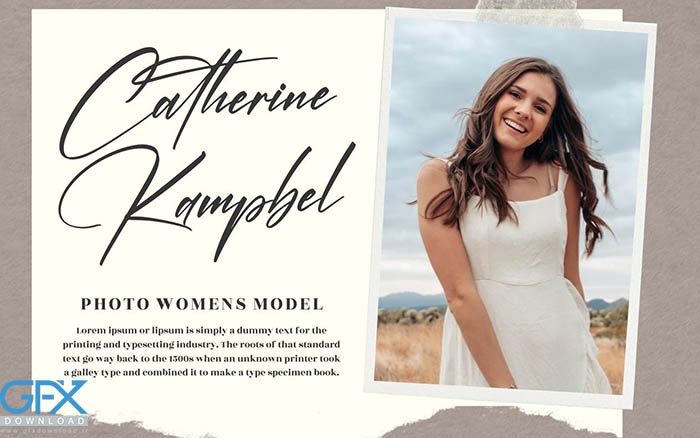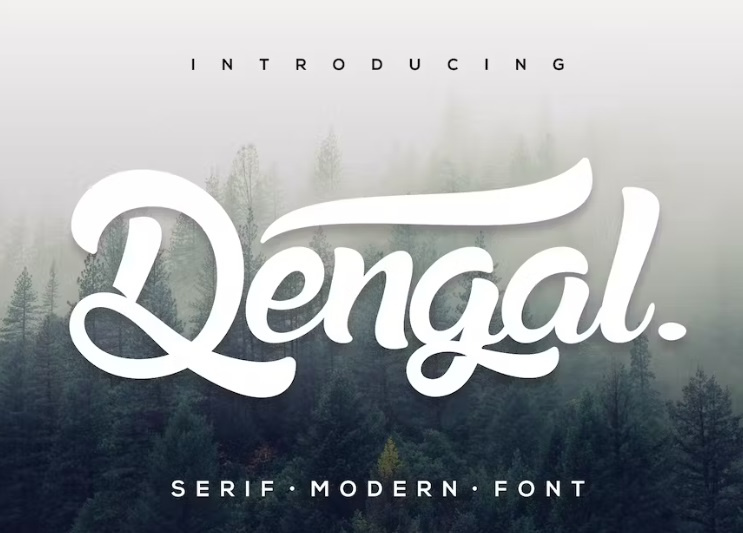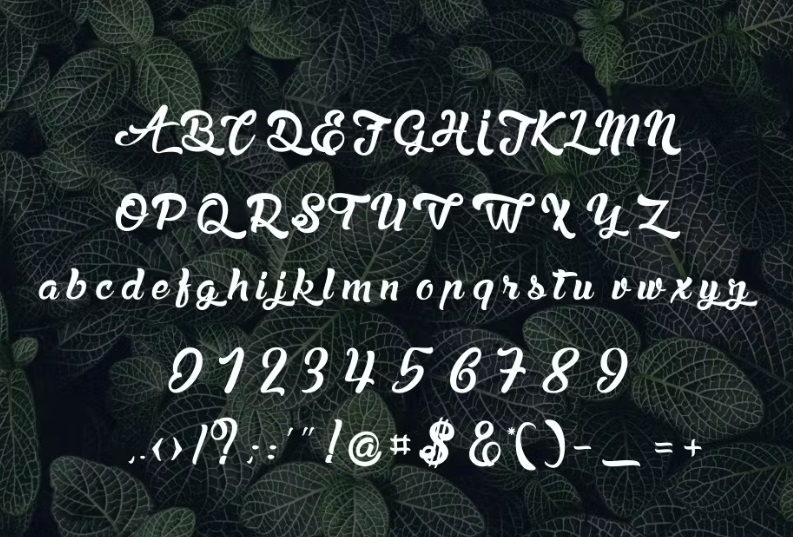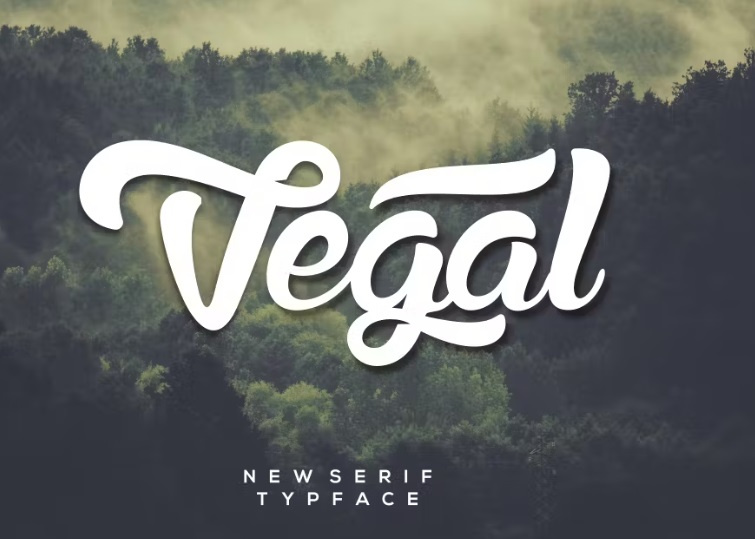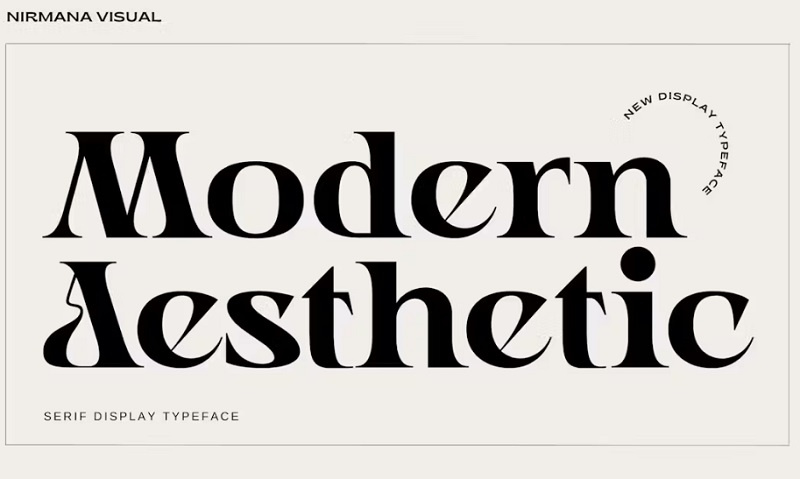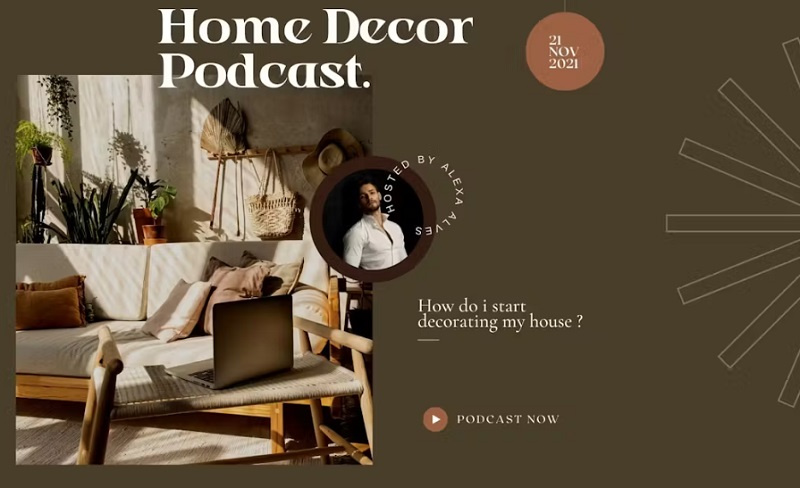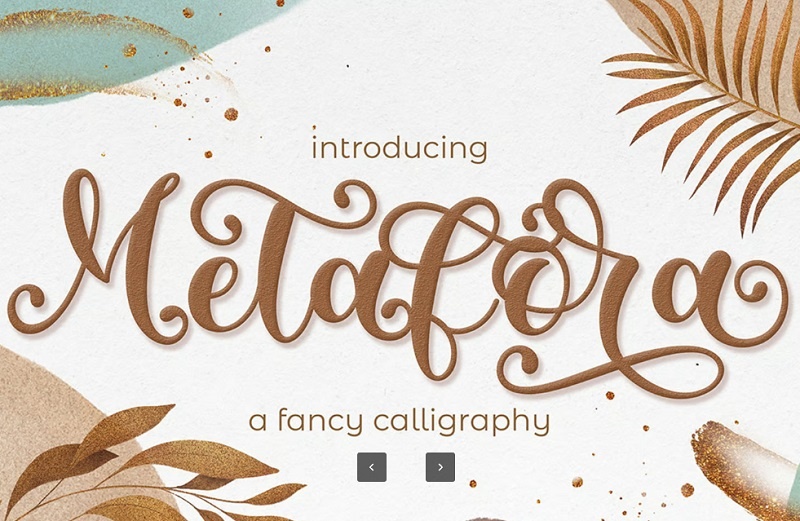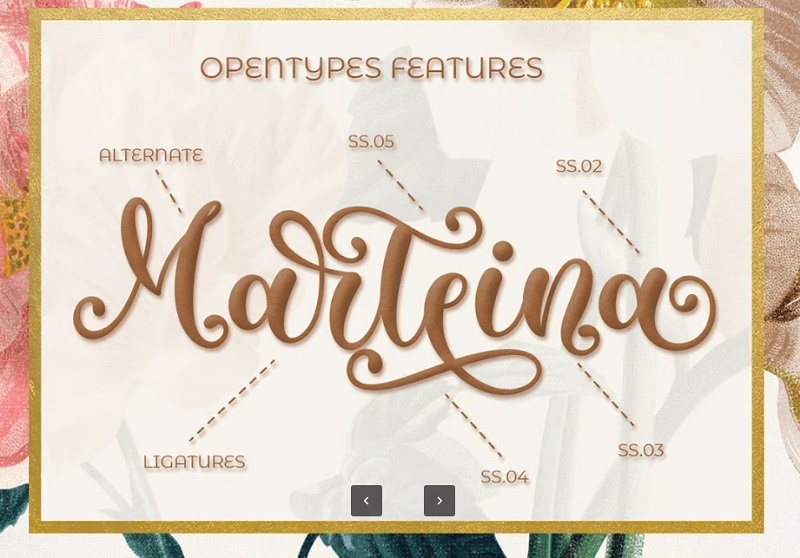
دانلود 4 فونت انگلیسی مدرن Cantika Beauty
فونت مدرن Cantika Beauty
1- دانلود فونت انگلیسی مدرن Cantika Beauty
یکی از فونت های انگلیسی، زیبا و مدرن است که برای تکمیل محصولات خلاقانه دیجیتال و چاپی شما مناسب است. فونت انگلیسی مدرن Cantika Beauty برای پوسترها، پست های رسانه های اجتماعی، برندسازی، پروژه های شخصی و غیره عالی است. شامل فرمت های OTF - WOFF - TTF می باشد.
فونت های مدرن انگلیسی Modern Aesthetic
2- فونت های مدرن انگلیسی Modern Aesthetic
Modern Aesthetic یک فونت تایپوگرافی زیبا برای انواع پروژه های طراحی، از جمله لوگو و برندسازی، پست های رسانه های اجتماعی، تبلیغات و طرح های محصول می باشد. برای دانلود فونت انگلیسی مدرن از جی اف ایکس دانلود در ادامه با ما همراه باشید.
فونت انگلیسی ساده مدرن Metafora
3- فونت انگلیسی ساده مدرن Metafora
Metafora یک فونت انگلیسی ساده مدرن مناسب برای طراحی های گرافیکی و تبلیغاتی، عروسی، کریسمس، لوگو و غیره می باشد. شامل فایل های OTF و TTF می باشد. فونت‌های انگلیسی ساده و مدرن، با خطوط تمیز و خوانایی بالا، انتخابی محبوب برای طراحان و گرافیست‌ها شده‌اند.
ویژگی های فونت انگلیسی مدرن از جی اف ایکس دانلود
✅ نام فونت انگلیسی 1: Cantika Beauty
✅ نام فونت انگلیسی 2: Dengal Modern
✅ نام فونت انگلیسی 3: Modern Aesthetic
✅ نام فونت انگلیسی 4: Metafora Modern Calligraphy